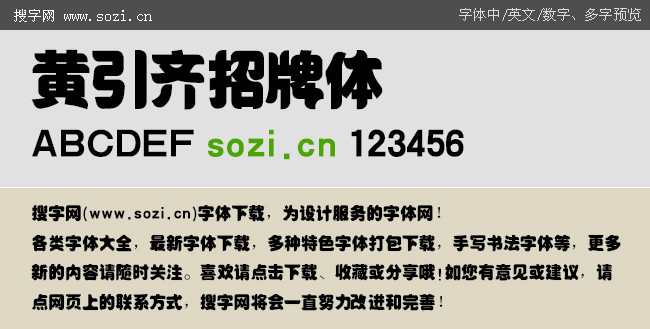
黃引齊招牌體
搜字網(wǎng)給大家提供一款黃引齊招牌體中文字體下載,黃引齊招牌體是一款字體線條粗壯有力的字體,適用于畫冊(cè)設(shè)計(jì)、海報(bào)設(shè)計(jì)、包裝設(shè)計(jì)等場(chǎng)合使用。(本字體為個(gè)人非商用版,如需要商用請(qǐng)聯(lián)系作者購(gòu)買版權(quán))